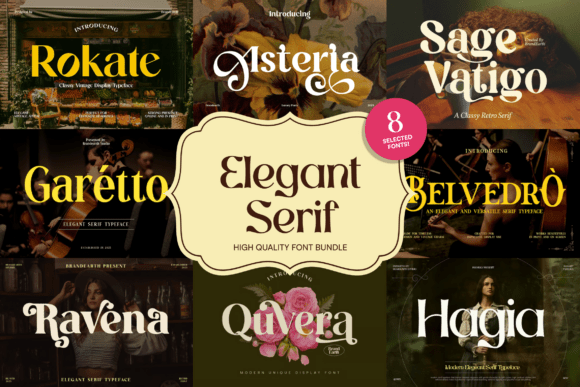
Elegant Serif Bundle
หากคุณกำลังมองหาเนื้อหาคุณภาพสูงเช่น Elegant Serif Bundle แพ็คเกจพรีเมียมนี้เป็นตัวเลือกที่ยอดเยี่ยมสำหรับโปรเจ็กต์สร้างสรรค์ของคุณ
ไม่ว่าคุณจะสร้างผลิตภัณฑ์ POD (Print on Demand) คำเชิญงานแต่งงาน หรือกราฟิกโซเชียลมีเดีย Elegant Serif Bundle ก็เหมาะสมอย่างยิ่ง